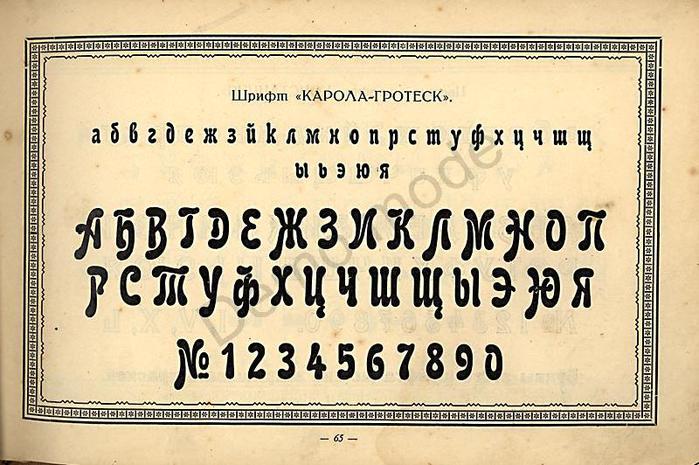
Рубленные шрифты без засечек, Гротески (Sans Serif, Grotesque fonts) на BestFonts.pro
У рубленых шрифтов отсутствуют засечки на концах букв, что считается их главной особенностью. Первые гротески появились в 1816 году и применялись, чтобы привлекать внимание к заголовкам и рекламным объявлениям. В основе современных комплектов типографских литер лежит система символов Akzidenz-Grotesk от компании Berthold.
С XX века и по сегодняшний день рублеными шрифтами преимущественно пользуются для акциденции и текстового набора. Наибольшую популярность обрели семейства Uni, Helvetica и Franklin Gothic. В целом гротески принято делить на 7 основных видов, к которым относятся следующие.
- Старые – шрифты простой и грубой формы. Бывают открытыми, полузакрытыми или моноширинными. Строчные буквы с крупным очком. В семейство входят, как прямые, так и наклонные гротески.
- Новые – более изящные версии предыдущих шрифтов, которые характеризуются отсутствием ярко выраженных отличительных черт.
Выносные элементы верхней части имеют аналогичный прописным символам кегль. - Открытые – современные гротески с малым контрастом и преобладанием негеометрических форм. Вертикальные штрихи со скошенными срезами встречаются только у этого типа рубленых шрифтов.
- Антиква-гротески – нечто среднее между гротесками и классическими шрифтами из времён эпохи Возрождения. На концах шрифтовых штрихов размещаются мелкие утолщения или засечки.
- Геометрические – шрифты с применением простых фигур вроде кругов или квадратов. Данный вид гротесков создали немецкие художники под влиянием дизайн-школы Баухауз и зародившегося в Советском Союзе конструктивизма.
- Моноширинные – спецшрифты с одинаковыми по толщине символами. Гротески используются в случаях, когда колонки и знаки должны совпадать по вертикали набора. Например, это актуально для программных листингов или вёрстки таблиц.
- Гуманистические – гротески с пропорциями, структурой и формой, которые основываются на старостильной антикве.
Шрифты создаются с открытым рисунком и незначительным межштриховым контрастом.
Размеры шрифтов в приложениях UWP масштабируются автоматически на всех устройствах. Алгоритм масштабирования позволяет добиться того, что шрифт размером 24 пикселя на Surface Hub, который располагается на расстоянии трех метров от пользователя, будет таким же читаемым, как и шрифт аналогичного размера, отображаемый на телефоне с диагональю экрана 5 дюймов, который располагается на расстоянии нескольких сантиметров от пользователя.
В силу особенностей работы системы масштабирования вы работаете с эффективными пикселями, а не физическими пикселями, и вам не следует изменять размер шрифта для различных размеров и разрешений экрана.
Используйте размер шрифта меньше 12 точек.
Иерархия
Пользователи полагаются на визуальную иерархию при просмотре страницы, когда заголовки представляют сводку содержимого, а основной текст содержит более подробные сведения. Чтобы создать четкую визуальную иерархию в приложении, используйте набор шрифтов Windows.
Набор шрифтов
Набор шрифтов Windows определяет важные отношения между начертаниями шрифтов на странице, помогая пользователям легко читать содержимое. Все размеры указываются в эффективных пикселях и оптимизированы для приложений UWP, работающих на всех устройствах.
Дополнительные сведения см. в руководстве по использованию увеличения типа XAML .
5. СовременностьТакие надписи узнаваемы по легкости, динамике, нарочитой небрежности и неожиданному использованию привычных элементов.